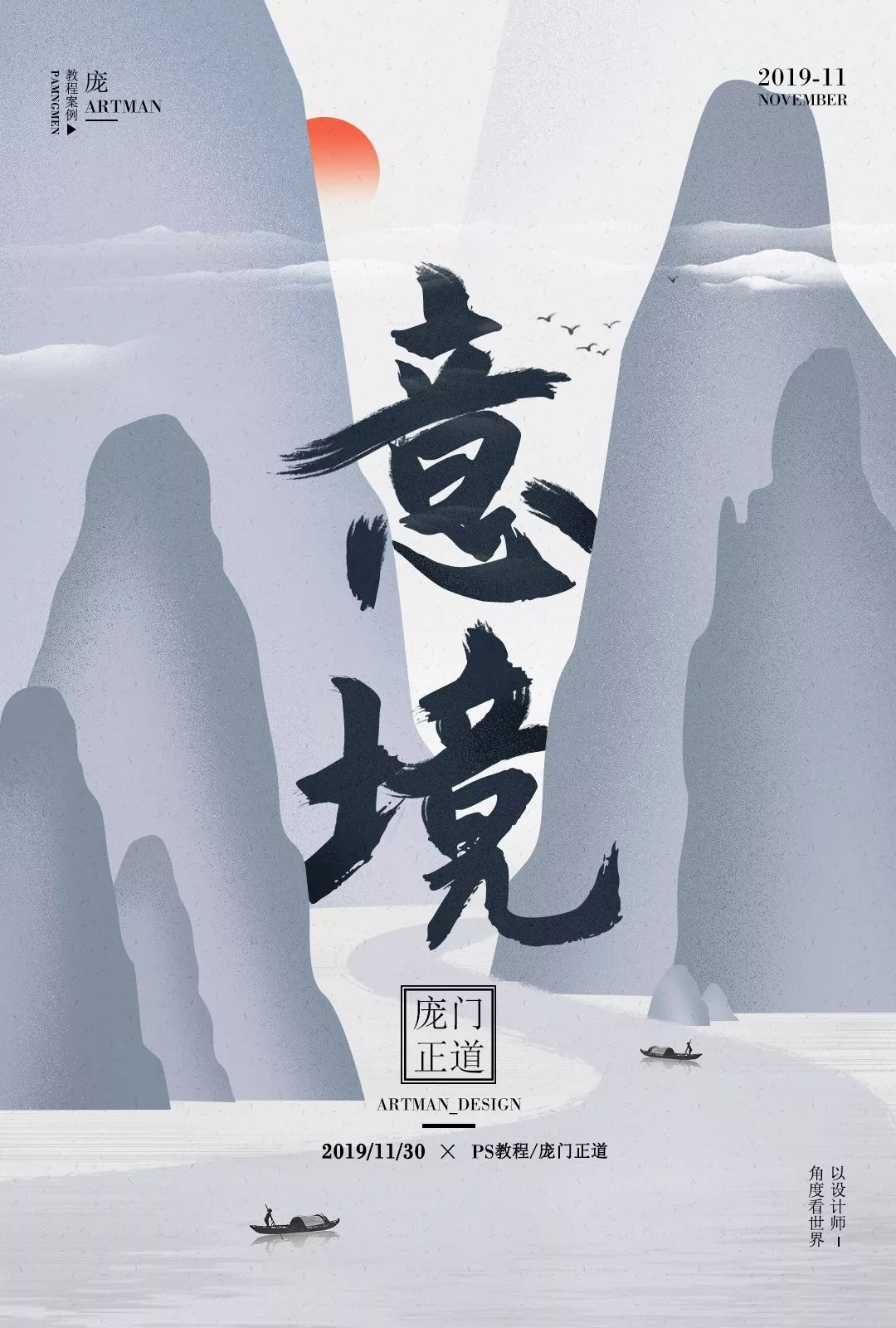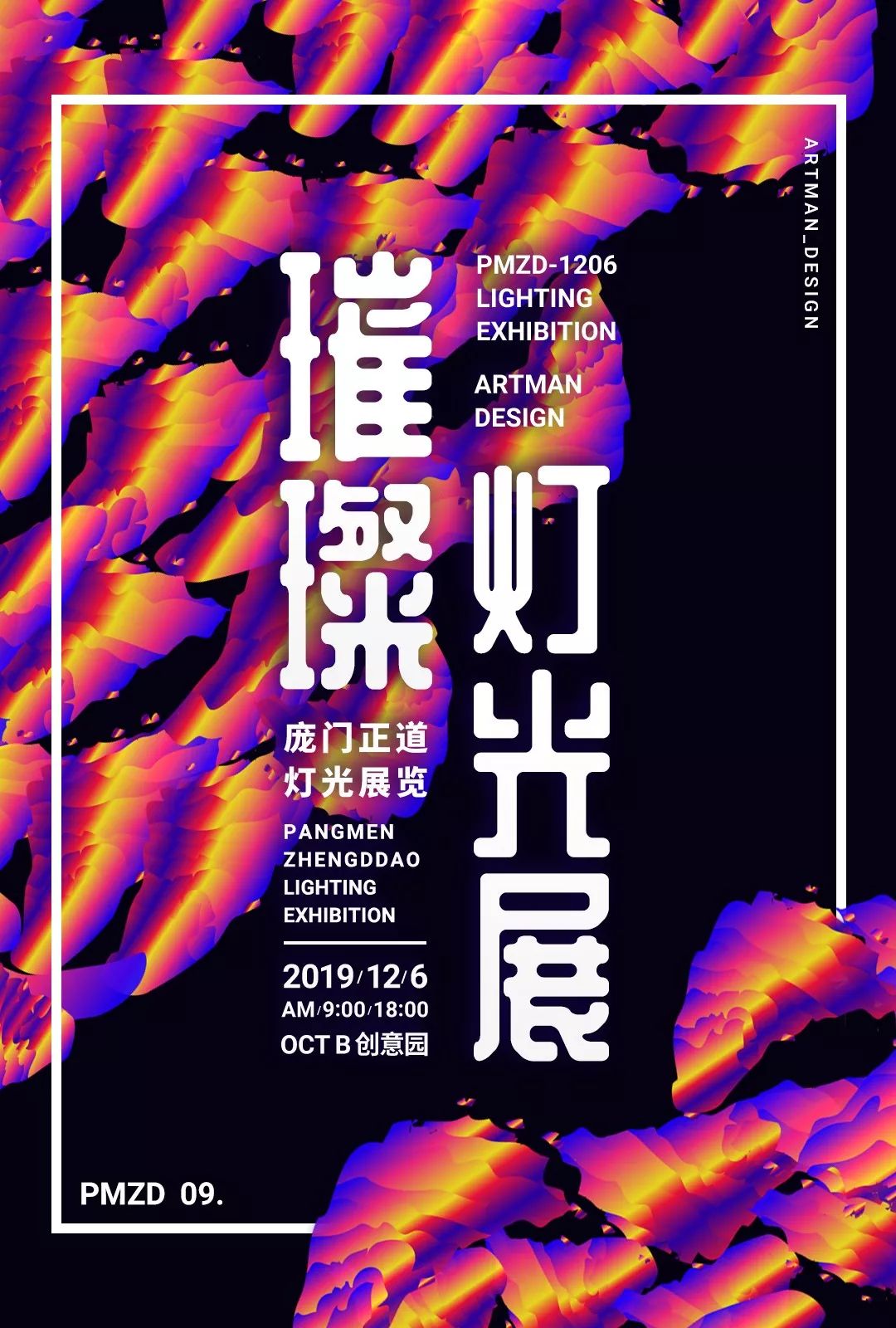
原来AI笔刷是这么用的?AI笔刷制作海报教程
今天教大家利用AI笔刷
实现下面海报效果
有同学会问AI笔刷哪里好?
AI笔刷是矢量的可以任意放大缩小
随意更改形状不变形
心动了吧,预备备开课
AI画笔在哪里?
菜单:窗口-画笔 在这里
先简单画一条直线,然后打开画笔对话框下面的画笔库菜单在弹出里找到矢量包-颓废画矢量包点开,弹出颓废画笔库这时就可以给直线进行画笔样式添加啦。
在勾勒一条复杂的线条添加颓废矢量线条样式,还开通过属性面板调整画笔粗细大小。
还可以用钢笔和直线勾勒出字形,在给字线条添加画笔样式。分分钟做出来自创书法字。
又可以选中画笔工具,选中颓废画笔矢量包其中一个画笔,画出字的轮廓书法字又分分钟完成了,老板再也不用担心我做字体侵权了。
这么简单知识点都要记好啊
打开画笔库下拉菜单,弹出里选中艺术效果-艺术效果-水彩,这时会弹出艺术效果-水彩库。
选中艺术效果-水彩库的任意一个画笔,用画笔工具在画布上随意勾勒。中途可以更换画笔,也可以随意放大缩小画笔大小。在框选中全部画笔,执行对象菜单下的扩展外观,给画笔填充合适颜色背景画面就做好了。
背景效果最终完成效果
利用画笔做海报背景也是分分钟完成啊
还不赶紧用起来!!
最后又到案例时间
用AI颓废画笔做毛笔字海报
再看下高清版